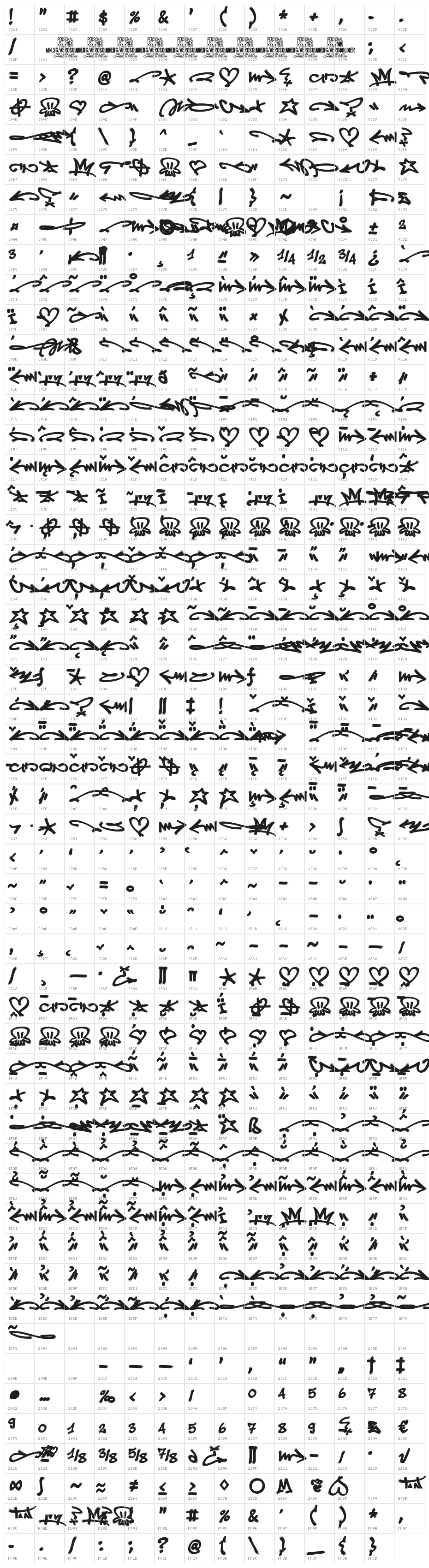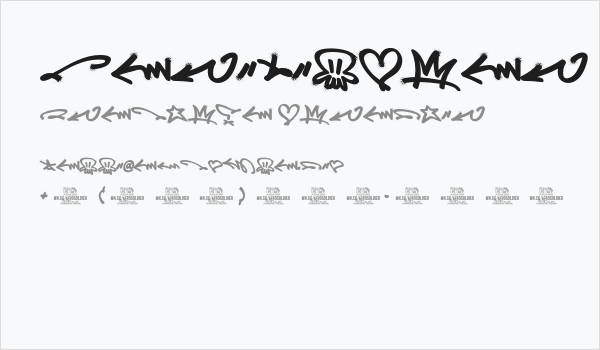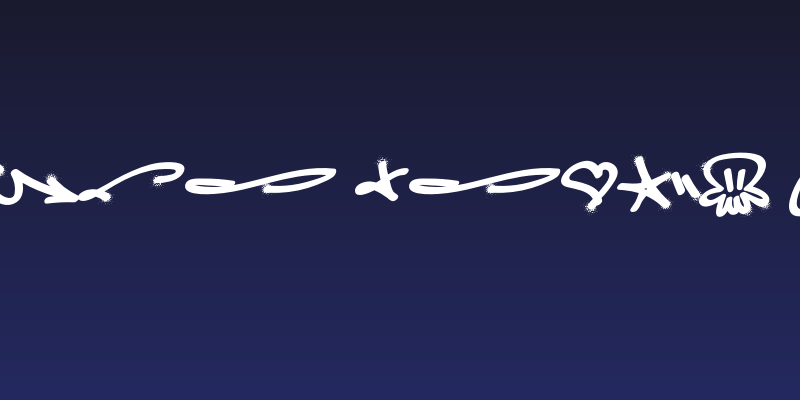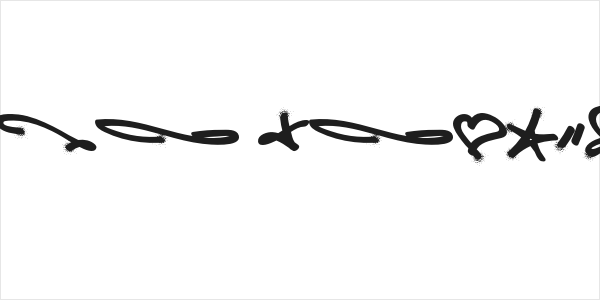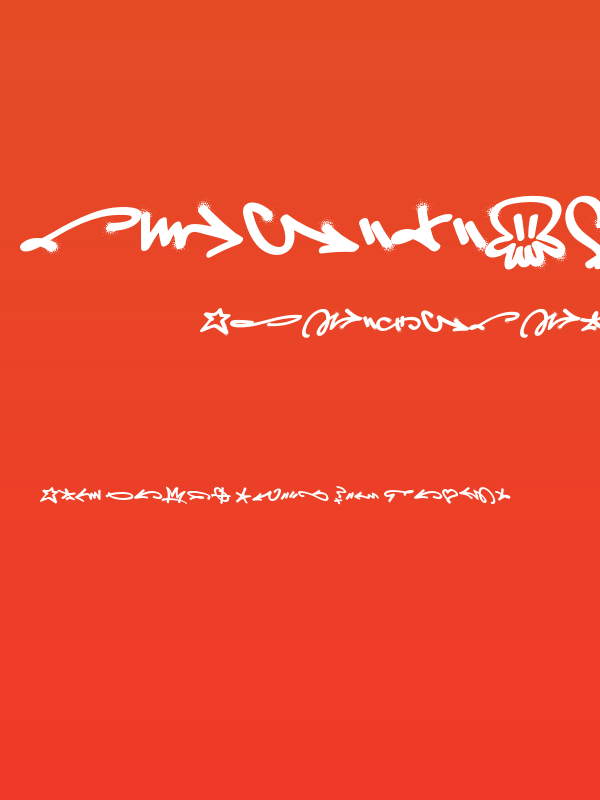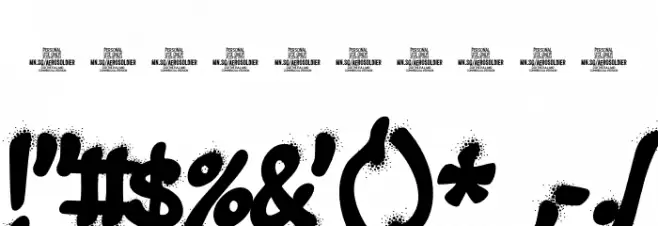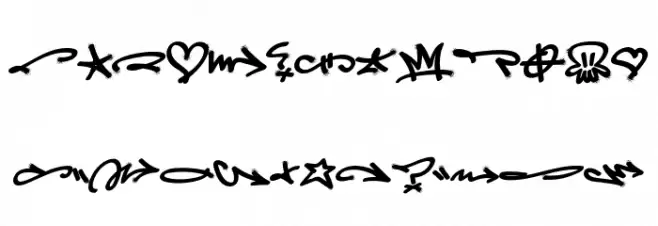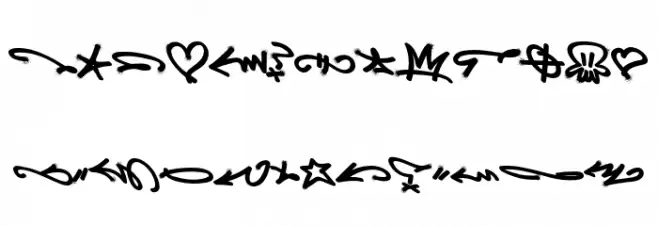
Aerosoldier Spray Symbol PERS Regular Font
| Gesamtstil | Decorative, Urban, Graffiti |
| Anwendungsfall | Logos, Posters, Headlines, Decorative elements |
| Vorgeschlagene Projekte | Street art posters, urban branding, event flyers, music album covers, youth-oriented designs. |